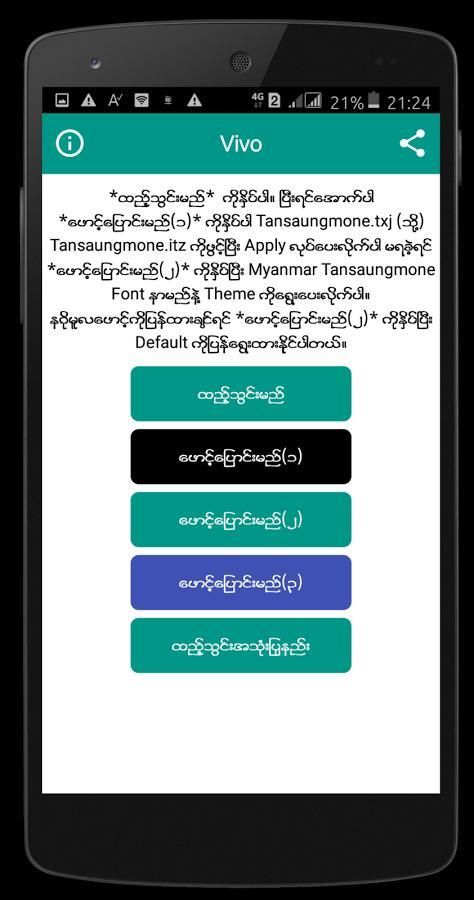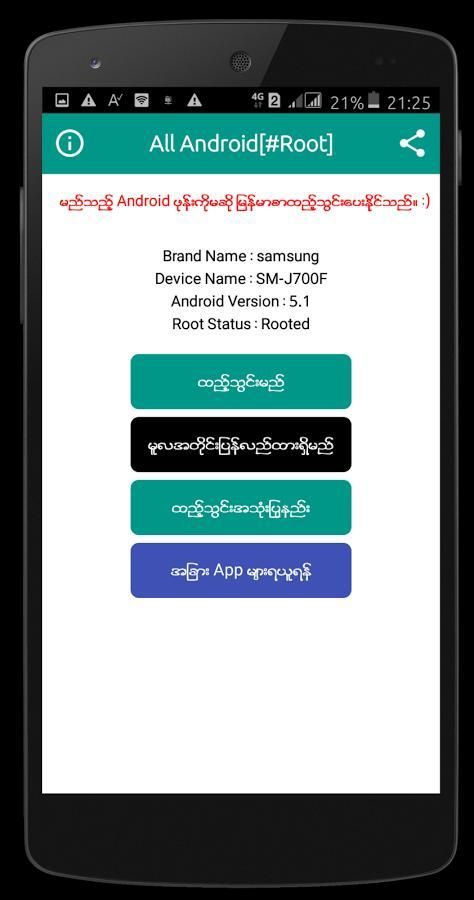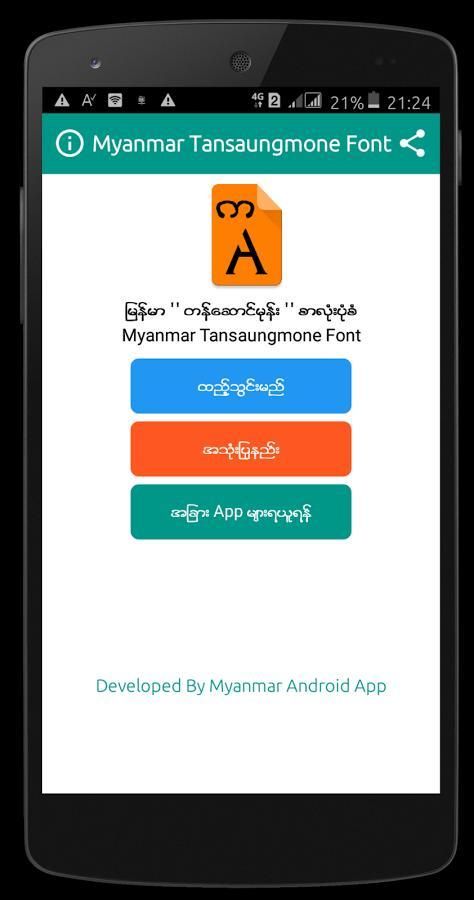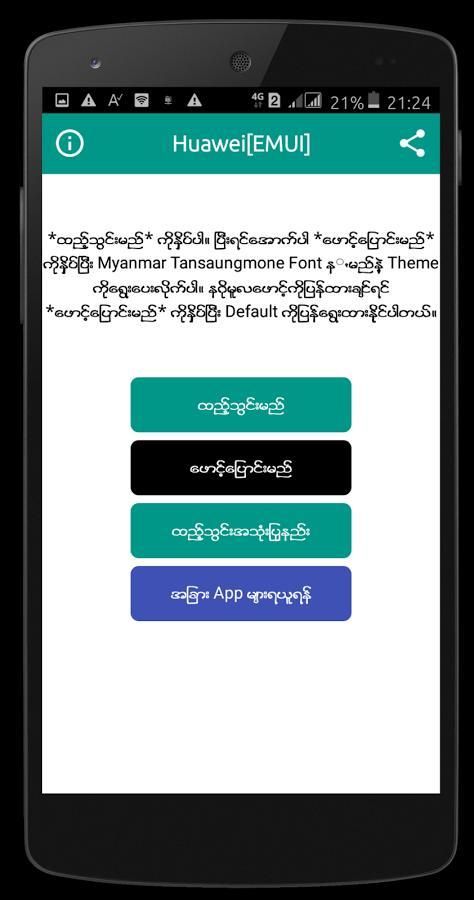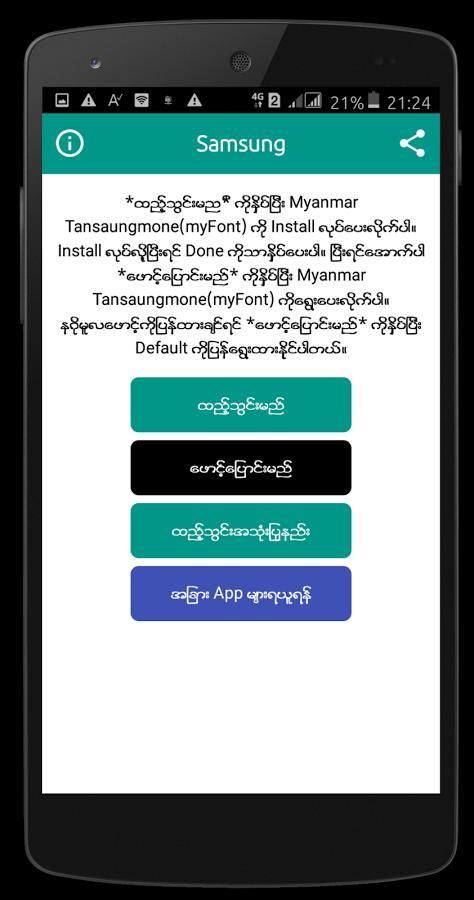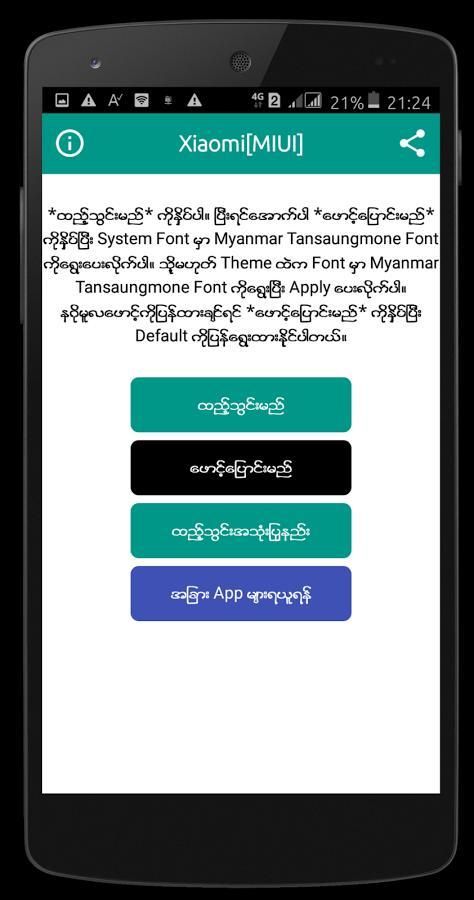
"Myanmar tansm Font" Root မလိုထည့္သြင္း ျမန္မာစာလုံးအလွတစ္ခုျဖစ္ပါသည္။
ဖုန္းမွာျမန္မာစာလုံးအလွသုံးခ်င္သူမ်ားအတြက္
Myanmar Tansaungmone ဆိုတဲ့စာလုံးအလန္းေလးတစ္ခုပါ။
အရမ္းလန္းပါတဲ့စာလုံးပုံစံေလးပါ။
"Myanmar Tansaungmone" Font is Beautiful Myanmar Zawgyi Font Style!